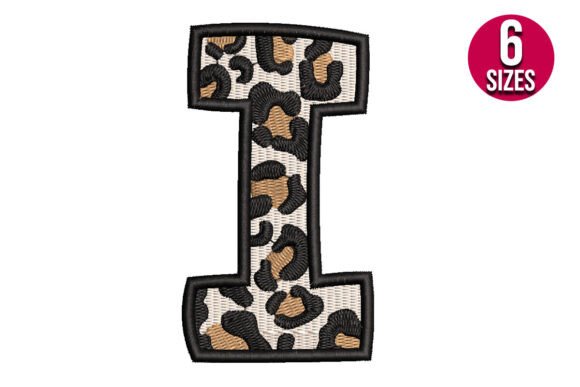
Leopard Print Alphabet Font Letter I
Trouver les bons éléments de conception peut être un défi, mais Leopard Print Alphabet Font Letter I propose une collection exceptionnelle qui rehausse instantanément votre travail.
Conçu avec précision, Leopard Print Alphabet Font Letter I offre des vecteurs nets, une typographie fluide et une licence commerciale pour une tranquillité d'esprit.
Que vous créiez des produits POD (impression à la demande), des invitations de mariage ou des visuels pour les réseaux sociaux, Leopard Print Alphabet Font Letter I est un choix idéal.